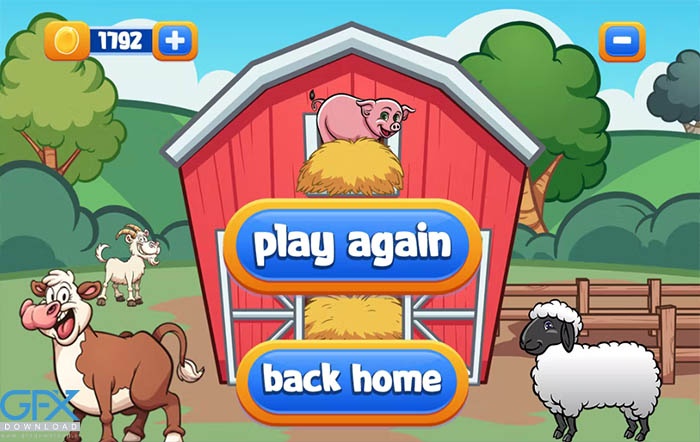
دانلود فونت بازی کودکان Pong Game
فونت بازی کودکان Pong Game
دانلود فونت بازی کودکان Pong Game مناسب انواع طراحی های کودکان شامل آلبوم کودک،بنر،کارت دعوت تولد کودکان و سایر طراحی های کودکانه دیگر می باشد. فونت عالی مناسب برای بازار کتاب های کارتونی، بازی های آنلاین، پوسترهای رویداد، فونت وسایل مدرسه، فونت های بسته بندی مواد غذایی، پوسترها، عنوان فیلم ها، جلدهای یوتیوب، تصاویر کوچک یوتیوب، جلد صفحات رسانه های اجتماعی و غیره...
فونت انگلیسی بازی کودکان Pong Game